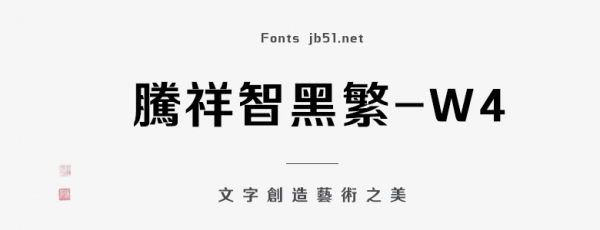
騰祥智黑繁-W4是一款不錯(cuò)的藝術(shù)字體,由騰祥字庫(kù)出品,這款字體屬于騰祥智黑系列字庫(kù),該系列一共有六款粗細(xì),以W1至W6命名,這款字體是智黑系列中較粗一款,適合應(yīng)用于藝術(shù)設(shè)計(jì)、平面宣傳設(shè)計(jì)、網(wǎng)頁(yè)設(shè)計(jì),書(shū)法字帖等領(lǐng)域,需要的朋友可以前來(lái)本站下載。
騰祥智黑系列字庫(kù)是騰祥睿黑系列字庫(kù)的兄弟篇,與睿黑風(fēng)格相近但排版效果迥異。該系列一共有六款粗細(xì),以W1至W6命名。智黑系列更強(qiáng)調(diào)了黑體的特征,筆畫(huà)簡(jiǎn)潔、硬朗、穩(wěn)重大方。塔形頓點(diǎn)、撇點(diǎn)賦予了智黑特殊的設(shè)計(jì)效果,使智黑又區(qū)別于傳統(tǒng)的黑體,既具有黑體的魅力又具有一定的裝飾特色,使黑體具有了靈活、生動(dòng)的特點(diǎn),從而形成自己鮮明的特色。本款字庫(kù)為智黑系列較粗一款W4,適用于標(biāo)題、屏顯、設(shè)計(jì)類用字。